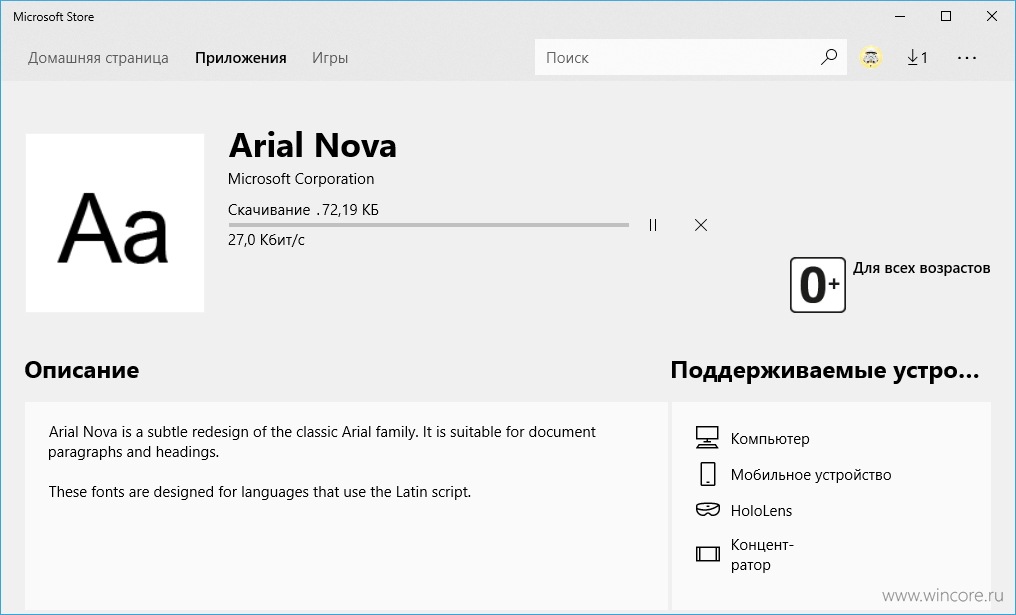
Microsoft будет публиковать в магазине ещё и шрифты
В начале этой недели мы узнали о планах Microsoft по распространению через магазин дополнительных языковых пакетов, сегодня в Microsoft Store были обнаружены ещё и шрифты, также опубликованные редмондской компанией. Что дальше? Может быть собственно Windows?
В частности в разделе Приложения → Персонализация одним из энтузиастом Windows была обнаружена страница нового шрифта Arial Nova. Как утверждается в описании, он пригоден для использования в заголовках и параграфах документов, создан для языков, использующих латинское написание. После установки шрифт доступен во всех установленных приложениях, как и любой другой из коллекции Windows.
Microsoft будет публиковать в магазине ещё и шрифты
Для тех кто только подключился к нам, поясним: уже сейчас через магазин кроме приложений, игр, фильмов и книг распространяются темы оформления, дистрибутивы GNU/Linux, расширения для Microsoft Edge и других программ, дополнения для игр. С Redstone 4 там же будут запущены страницы языковых пакетов для интерфейса (а кроме того устройств линейки Surface и аксессуаров для них). Вероятно разработчики Windows 10 планируют перевести весь дополнительно устанавливаемый контент в Microsoft Store?